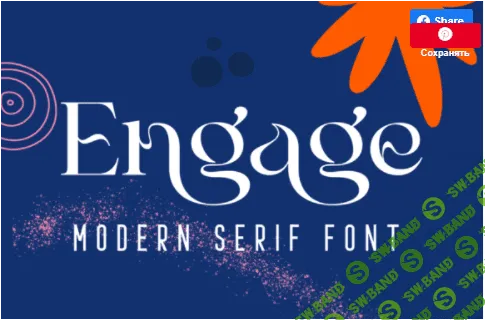
Автор: creativefabrica
Название: Engage Font (2022)
[creativefabrica] Engage Font (2022)
Engage — элегантный и стильный шрифт с засечками. Модный и уникальный, этот шрифт украсит каждое ваше творение. Engage имеет кодировку PUA, что означает, что вы можете легко получить доступ ко всем глифам и росчеркам!